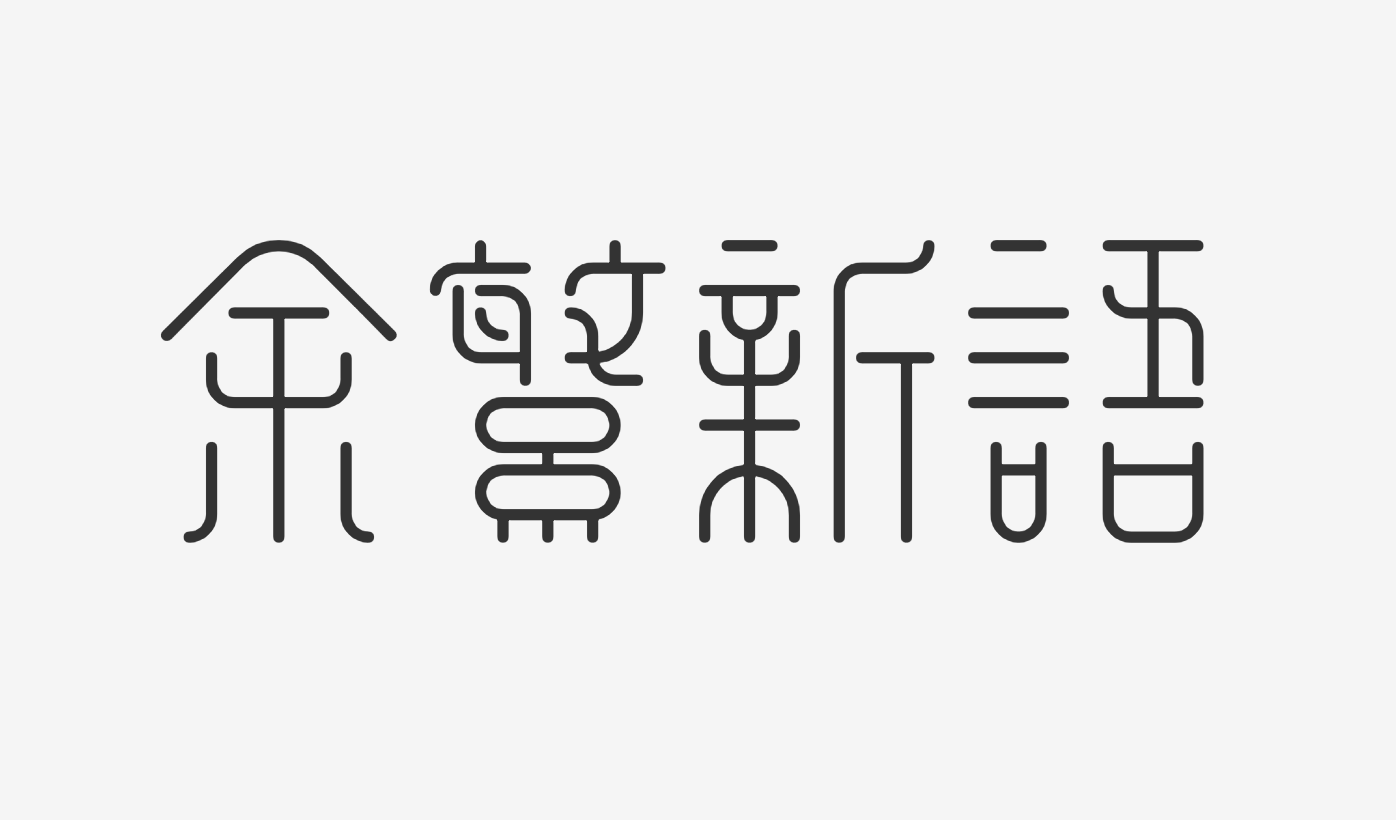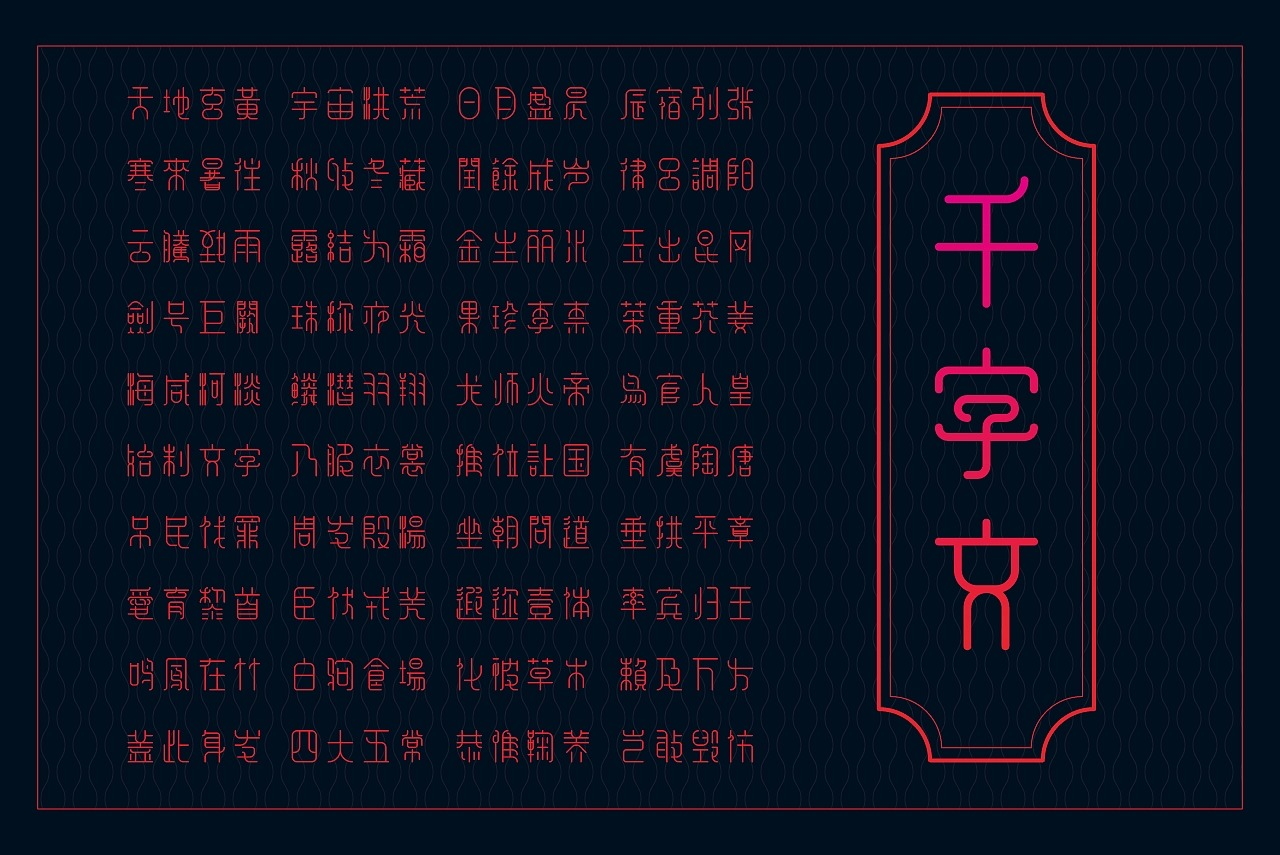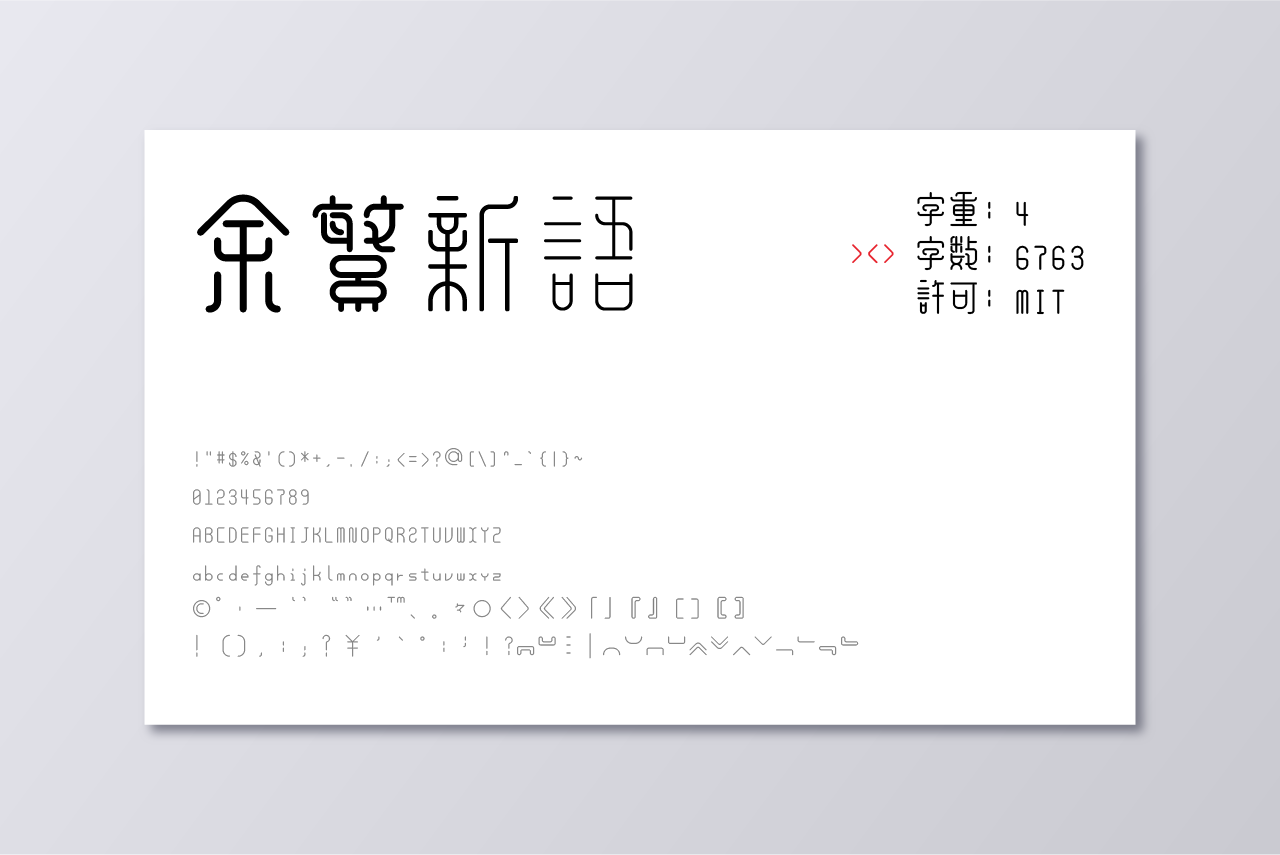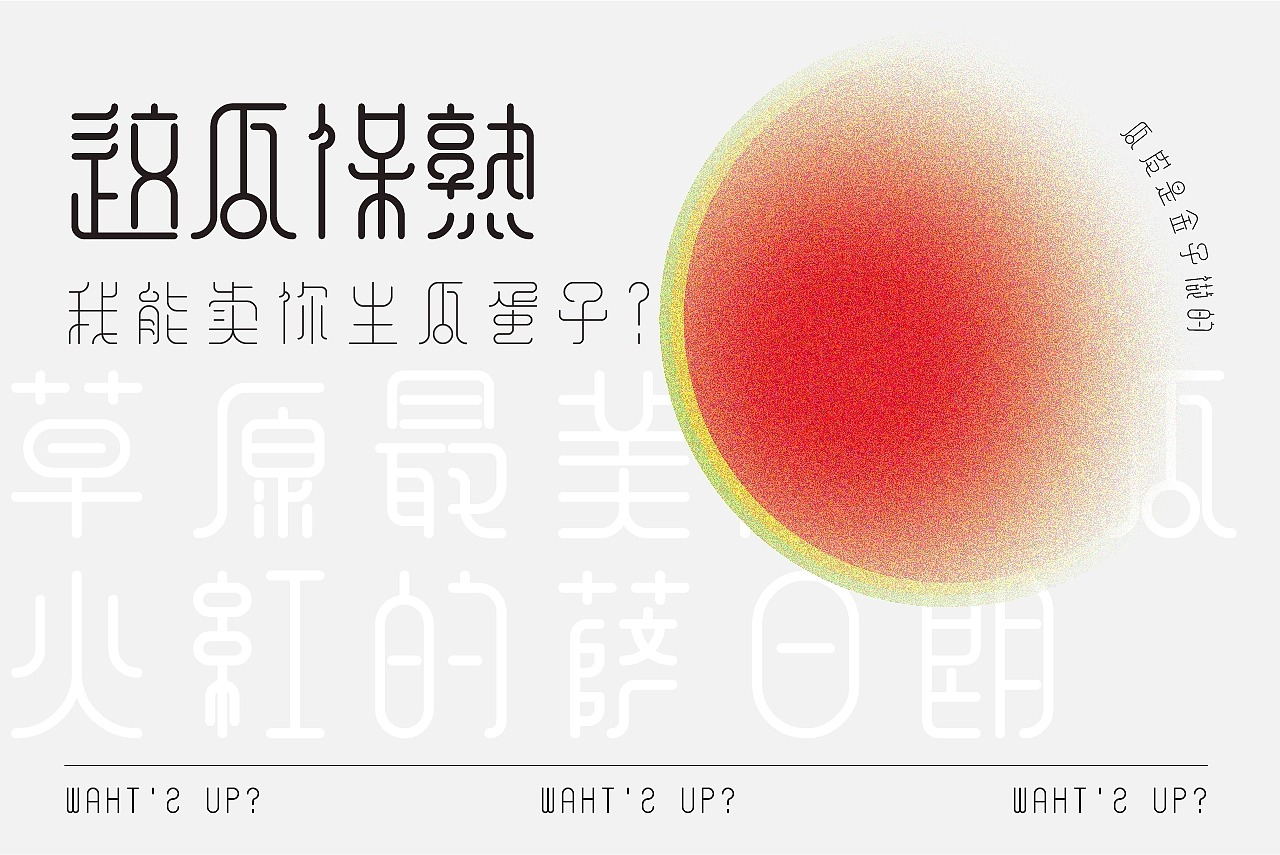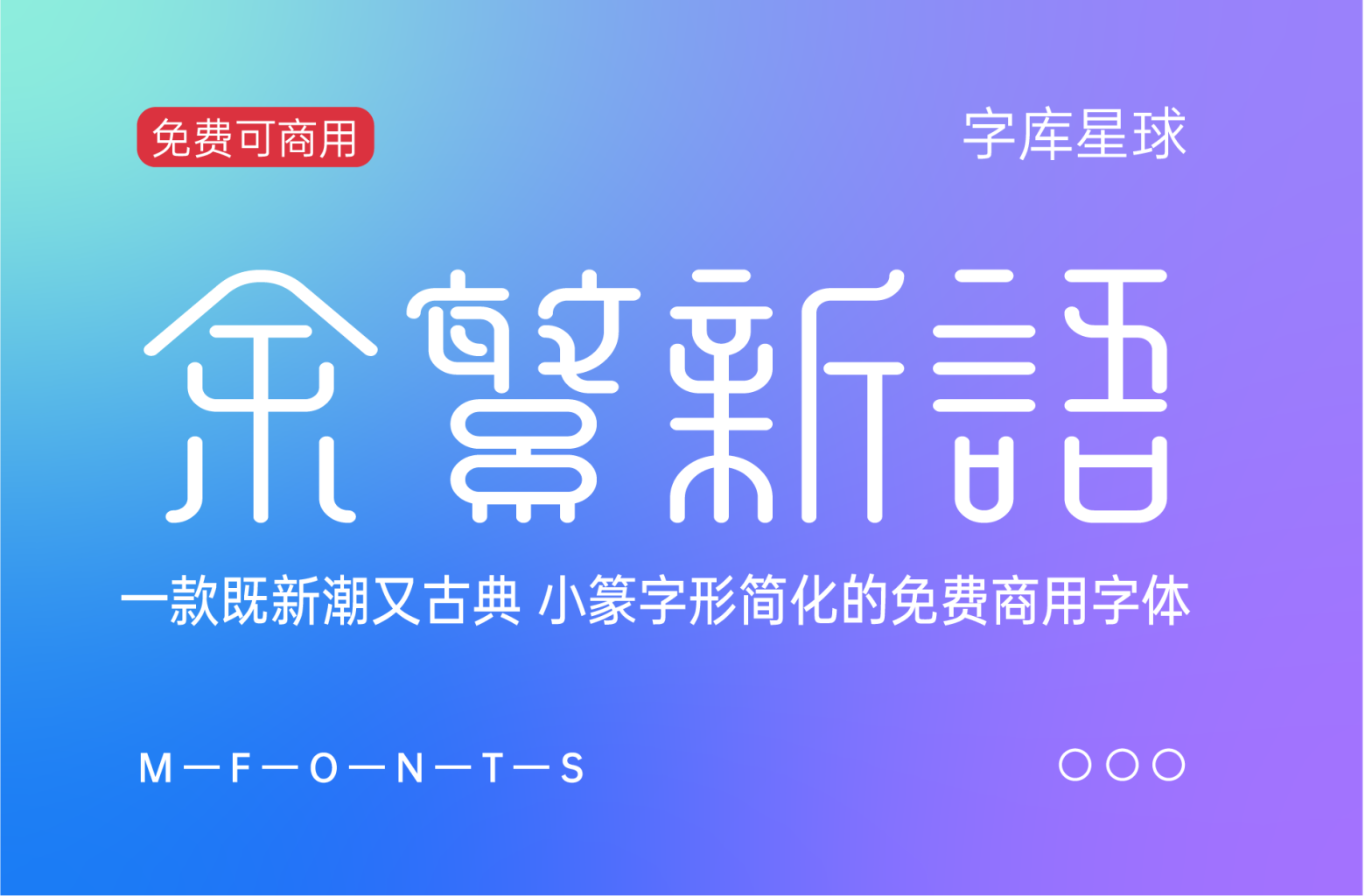
起因是客户想要一种既新潮又古典的字体
虽然嘴上说着不可能,但尝试把小篆字形简化后,客户却很满意
难道是我的态度有问题吗……
计划要做6763个常用字
把一个字形创意具现到几千个实例上是一件很考验耐心的工作
即使努力的优化了制作流程,不可避免的实际工作仍要消耗一个半月的时间
累了,字体展示就随意一些吧
字体展示
文章标题:余繁新语